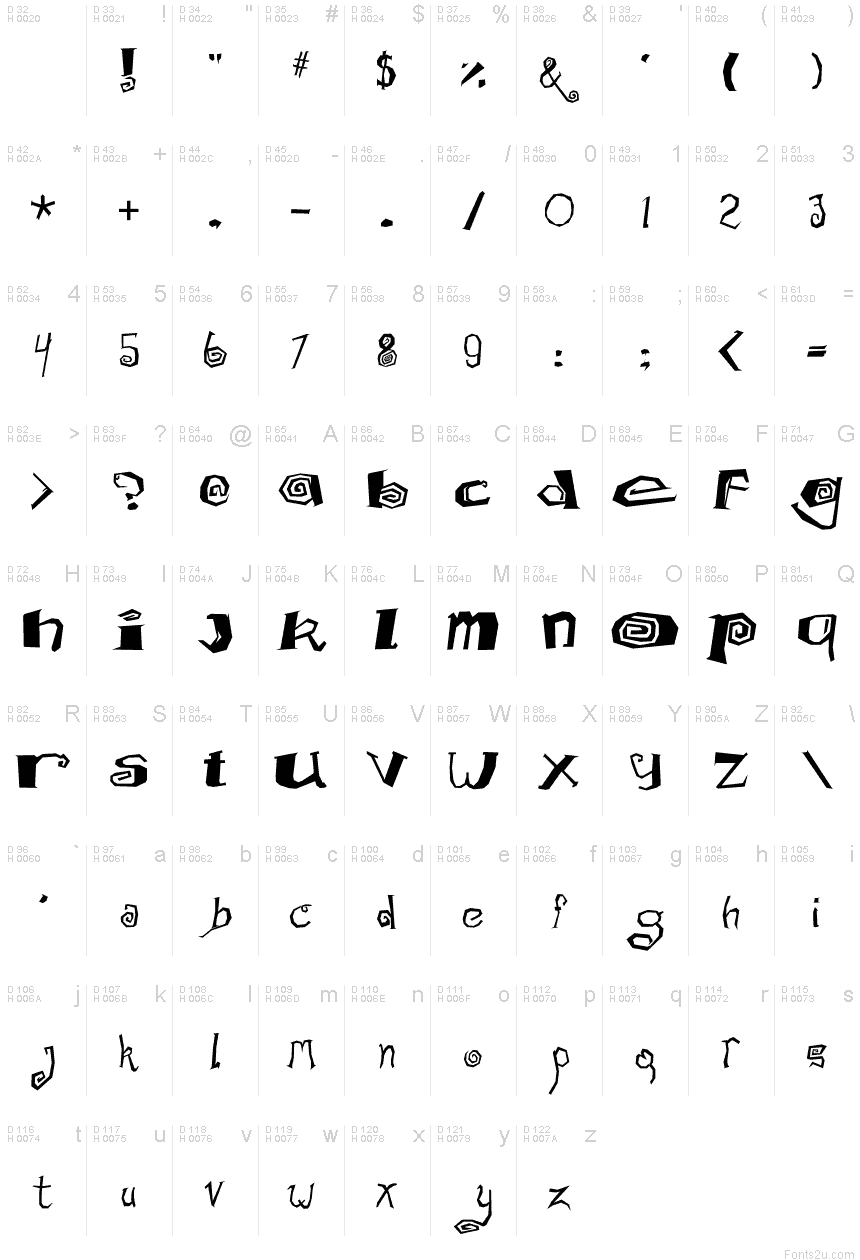
Math Donuts to darmowy font typu display, utrzymany w stylistyce ręcznie wycinanego papieru. Jego nieregularne kształty łączą ostre kąty z kilkoma zakręconymi detalami. Całość sprawia wrażenie celowo nierównej i nieco zawadiackiej, nadając napisom energiczny, „bazgrolony” charakter przy zachowaniu graficznej spójności.
Math Donuts świetnie sprawdzi się w tytułach plakatów, materiałach edukacyjnych, ulotkach, naklejkach, menu gier czy wesołych projektach logo. Jego oryginalna konstrukcja nadaje krótkim frazom żywego rytmu – to idealny wybór, gdy zależy Ci na liternictwie o domowym, autentycznym wyrazie, a nie na wygładzonym, technicznym kroju.